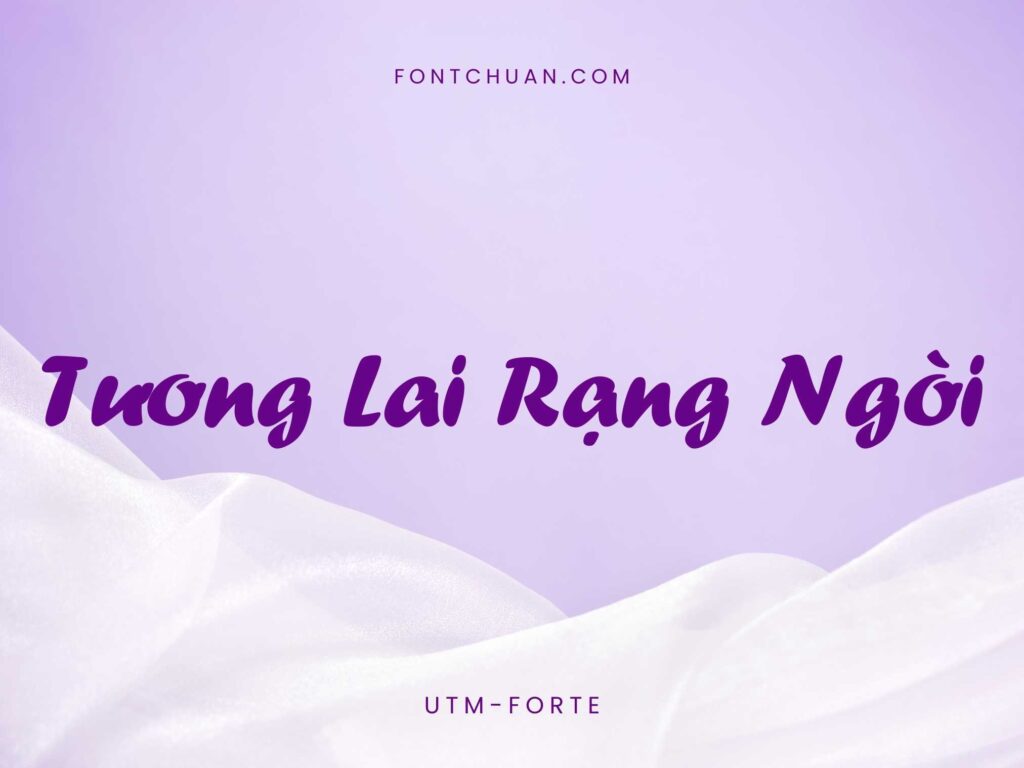
Font UTM Forte Việt Hóa
Font UTM Forte Việt Hóa là một kiểu chữ script mạnh mẽ, mang phong cách viết tay năng động và đầy cá tính. Với đường nét dày dặn, uốn lượn mượt mà và cảm giác tự nhiên, font này là sự lựa chọn hoàn hảo cho các thiết kế cần sự nổi bật, sáng tạo và mang đậm phong cách cá nhân.
Font này đã được Việt hóa để hỗ trợ đầy đủ tiếng Việt bởi Thiên Minh, ngoài ra còn hỗ trợ hơn 200 ngôn ngữ khác. Thành viên của Font Chuẩn đã sưu tầm và chọn lọc font này nhằm đáp ứng nhu cầu của người dùng trong thiết kế và ứng dụng thực tế. Font có đặc điểm nổi bật với kiểu chữ dày, khỏe khoắn, phù hợp với các dự án như thiết kế logo, bìa sách, poster quảng cáo và nhiều lĩnh vực sáng tạo khác.